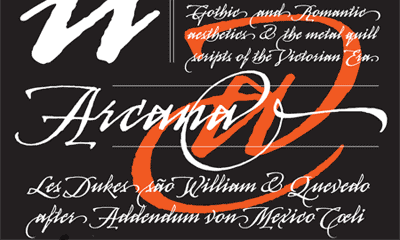
Language Culture Type
Книга Language Culture Type была выпущена во время первого международного
конкурса шрифтового дизайна "bukva:raz". Целью проводимого конкурса была
пропаганда плюрализма и многообразия культур, взаимодействия и
сотрудничества в области типографики.
Книга подробно представляет работы победителей, включая информацию о
кодировке и дизайнере шрифта. В книге имеется несколько статей дающих
представление о взаимодействии шрифтов и мировых языков на данный момент,
включая попытку охватить все существующие письменности в одну систему
цифрового кодирования, названную Unicode.
Так же в книге рассмотрены специфические проблемы разрабтки шрифтов для большинства
мировых лингвистических культур, начиная от различных Кириллических
буквенных форм, заканчивая древним Вьетнамским идеографическим письмом.